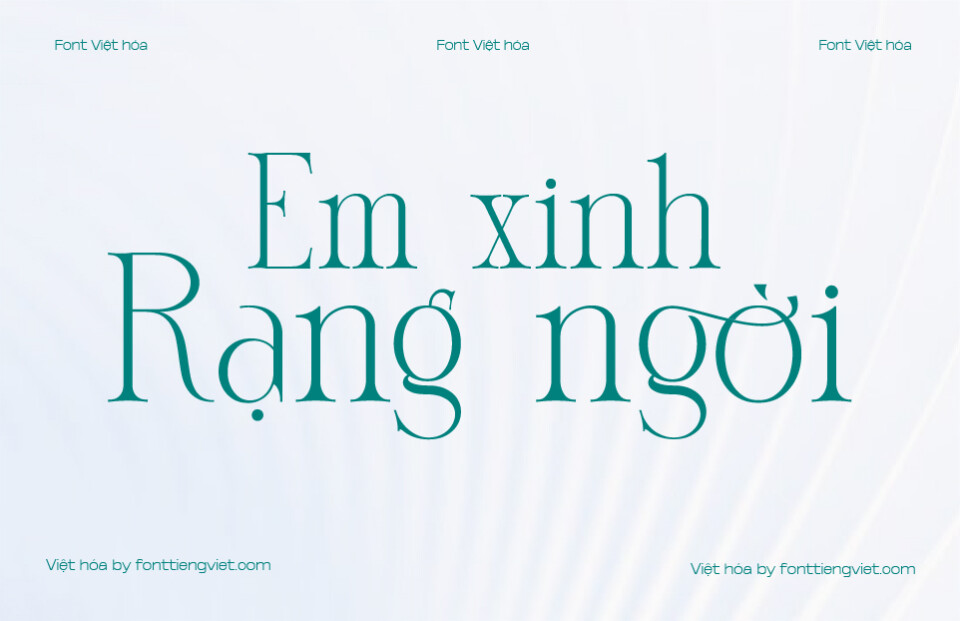
Font Việt hóa 1FTV VIP Morgina Regular
Giới thiệu về Font Việt hóa 1FTV VIP Morgina Regular
Trong thế giới thiết kế đồ họa hiện đại, việc lựa chọn một Font Miễn Phí chất lượng đóng vai trò then chốt giúp sản phẩm trở nên nổi bật và thu hút người xem hơn bao giờ hết. Một trong những cái tên đang gây chú ý mạnh mẽ trong cộng đồng designer Việt chính là Font Việt hóa 1FTV VIP Morgina Regular. Đây là một bộ font thuộc phân khúc cao cấp, được tinh chỉnh kỹ lưỡng để phù hợp với đặc điểm ngôn ngữ và thẩm mỹ của người dùng Việt Nam. Với phong cách Serif cổ điển kết hợp cùng những đường nét hiện đại, Morgina Regular mang đến một cảm giác sang trọng, thanh lịch nhưng không kém phần gần gũi. Việc sở hữu một bộ font được việt hóa hoàn chỉnh giúp người dùng loại bỏ hoàn toàn nỗi lo về lỗi hiển thị dấu tiếng Việt, từ đó tập trung tối đa vào sức sáng tạo của mình.
Đặc điểm nổi bật của Font Việt hóa 1FTV VIP Morgina Regular
Thiết kế sang trọng và tinh tế
Điểm ấn tượng nhất của Font Việt hóa 1FTV VIP Morgina Regular nằm ở cấu trúc hình học cân đối và các nét thanh nét đậm được xử lý mượt mà. Các chữ cái có độ rộng vừa phải, tạo cảm giác thoáng đãng và dễ đọc ngay cả khi sử dụng ở kích thước nhỏ. Đây là lựa chọn lý tưởng cho các bạn học sinh, sinh viên khi thực hiện các bài thuyết trình hay các thầy cô giáo soạn thảo giáo án điện tử cần sự chỉn chu và chuyên nghiệp. Sự kết hợp giữa nét truyền thống và hơi thở đương đại giúp font chữ này không bị lỗi mốt theo thời gian.
Khả năng ứng dụng đa dạng trong thực tế
Không chỉ dừng lại ở các văn bản thông thường, Font Việt hóa 1FTV VIP Morgina Regular còn tỏa sáng trong các dự án sáng tạo như thiết kế bìa sách, poster sự kiện trường học, hay các loại thiệp mời trang trọng. Nhờ vào bảng mã được tối ưu hóa, font chữ này hoạt động ổn định trên nhiều phần mềm thiết kế phổ biến như Adobe Photoshop, Illustrator hay thậm chí là các ứng dụng văn phòng cơ bản như Microsoft Word và PowerPoint. Điều này giúp cho bất kỳ ai, dù là người mới bắt đầu học thiết kế hay chuyên gia, đều có thể sử dụng một cách dễ dàng và hiệu quả nhất.
Cách tối ưu hóa Font Việt hóa 1FTV VIP Morgina Regular cho website
Để tận dụng tối đa vẻ đẹp của bộ font này trên môi trường số, người dùng nên chú ý đến việc kết hợp màu sắc và khoảng cách dòng. Việc sử dụng Font Việt hóa 1FTV VIP Morgina Regular làm tiêu đề chính sẽ tạo ra điểm nhấn thị giác cực mạnh, dẫn dắt người đọc đi sâu vào nội dung bài viết. Bên cạnh đó, bạn cũng có thể kết hợp nó với các font Sans-serif đơn giản để tạo ra sự tương phản hài hòa. Đừng quên kiểm tra độ tương phản giữa màu chữ và màu nền để đảm bảo nội dung luôn hiển thị rõ nét nhất trên mọi thiết bị di động và máy tính.